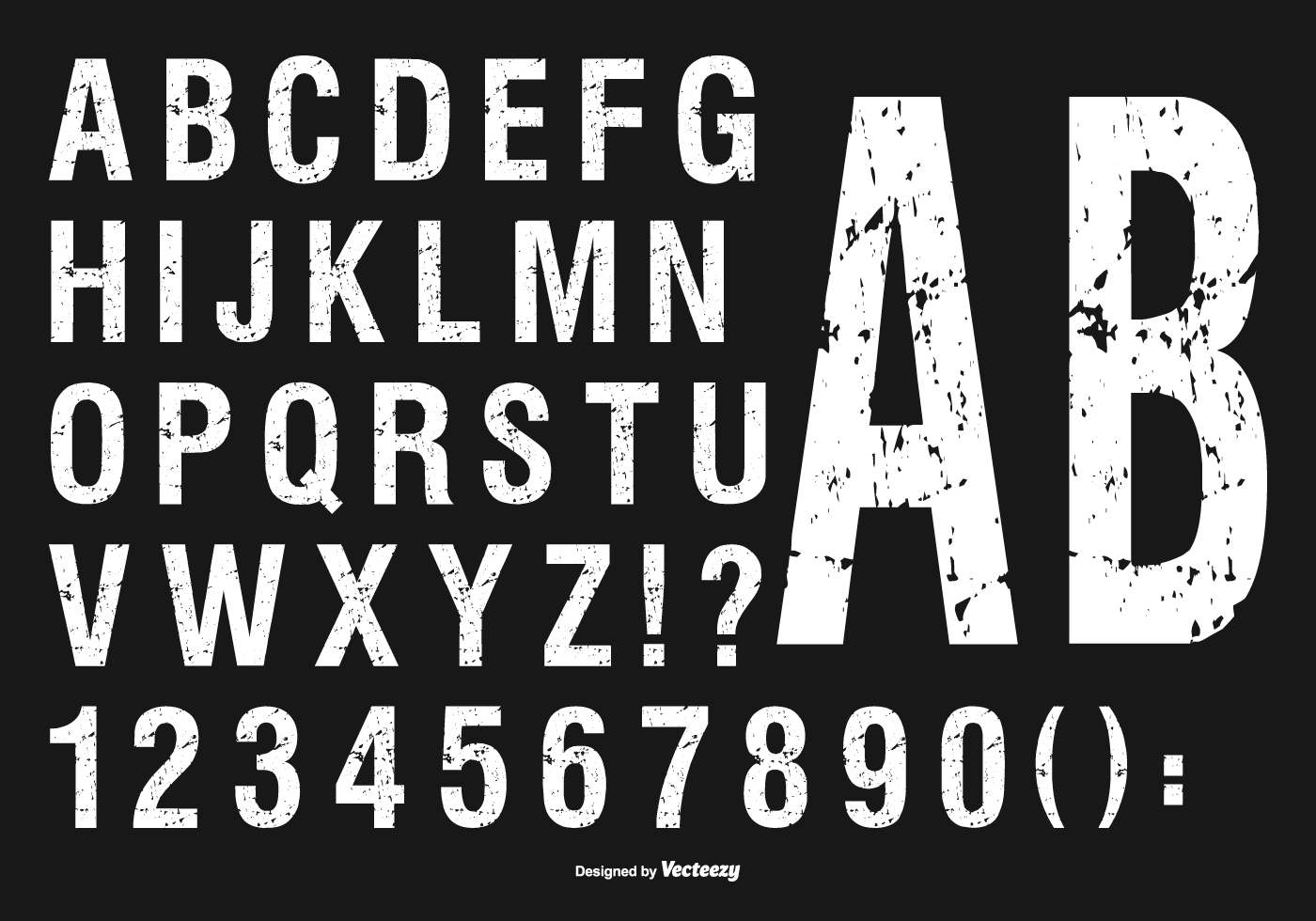
Это могут быть стикеры, полароидные снимки, обрывки бумаги, кусочки канцелярского скотча, скрепки, а также такие элементы, как кляксы, пятна, брызги и разводы на поверхности. В надписях на стенах или мебели используют «гранжевые шрифты», которые имеют потертости, заломы, шероховатости. Часто эти шрифты выглядят так, будто написаны от руки.
Может ли такая мелочь, как шрифт изменить значение слов или весь дизайн? Конечно!
Шрифт может добавить новый уровень тексту и значению вашего сообщения.![]()
Это может помочь вам наладить контакт с пользователем, сформировать бренд и задать тон всему проекту. Неправильный шрифт может сделать дизайн плоским, разрозненным или даже дать пользователям неверное представление о вашем бренде. Теперь, с этим знанием, давайте рассмотрим несколько примеров красивой типографики от Design Shack.
Настроение и сообщение, которое вы хотите донести должны соответствовать друг-другу
Может прозвучать странно, но это так: у каждого шрифта свое настроение. И точно также, как и ваше настроение, оно может меняться от окружения.
Это настроение помогает задать особенности проекта. Это обусловлено тем, что люди подумают о контенте. Это создает связь между тем, что вы делаете, и тем, кто вы и как люди реагируют на вас. (Слишком много давления для подписи, правда?).
Создание правильной связи начинается с понимания того, что вы хотите, чтобы нес ваш проект, а также немного знаний о разных стилях и истории шрифта.
Сравните сообщенияВы имели ввиду это?
Или пытались сказать это?
Единственная разница здесь в шрифтах.
Видите, насколько разные эти сообщения?
Нет определенной науки по сопоставлению шрифтов по настроению. На самом деле, в основном, это происходит интуитивно, и нужно просто посмотреть на шрифт и слово вместе, чтобы понять, что они несут (Если не верите в это, посмотрите на предыдущий пример).
Вот некоторые примеры, чтобы начать работу с разными стилями типографики:
- Шрифт с засечками (Serif): вечность, формальность
- Новостильная антиква (Modern serif): глянец, высокая мода
- Брусковый (Slab serif): важность, внимание
- Шрифт без засечек (Sans serif): нейтральный, простой
- Сжатый (Condensed): авторитетный, интенсивный